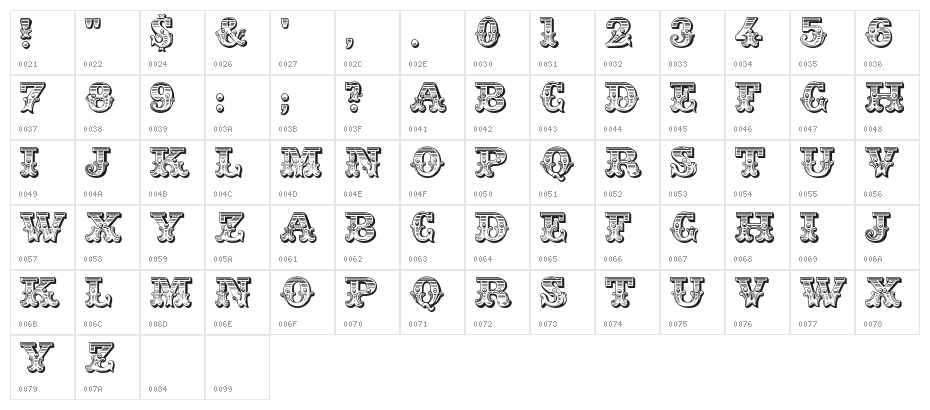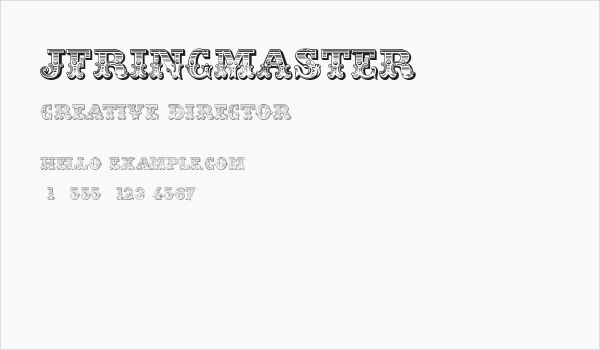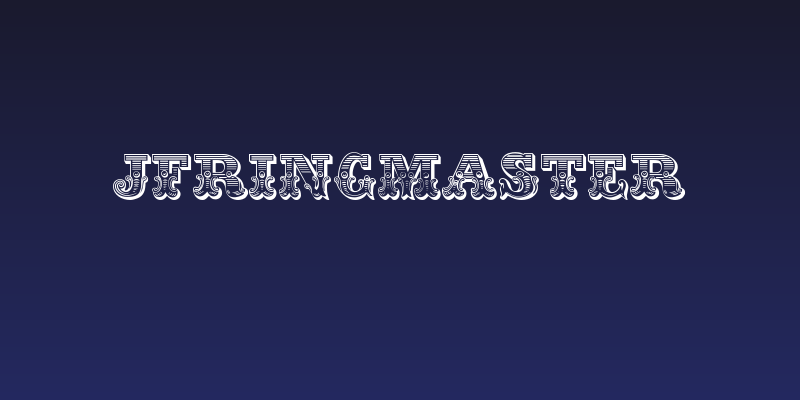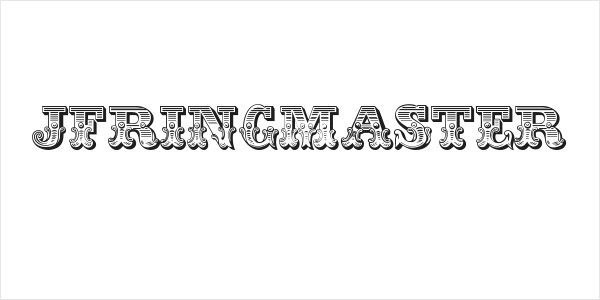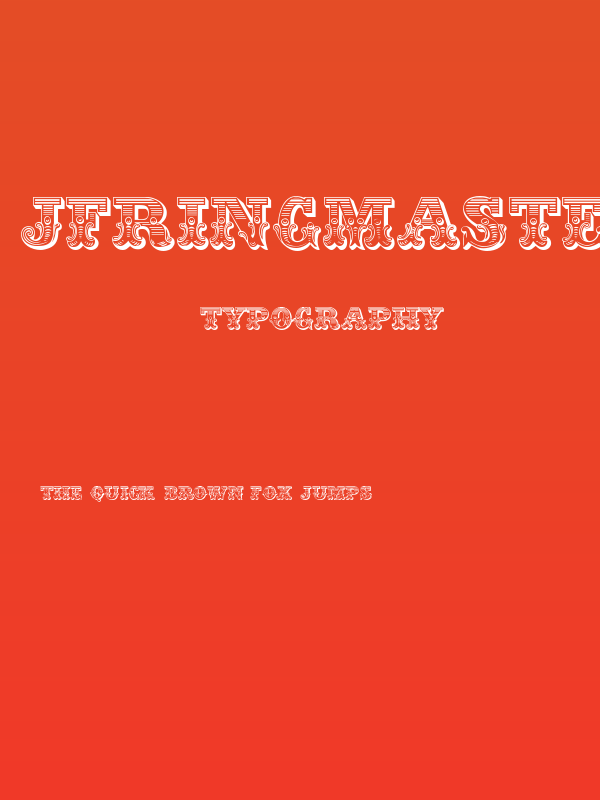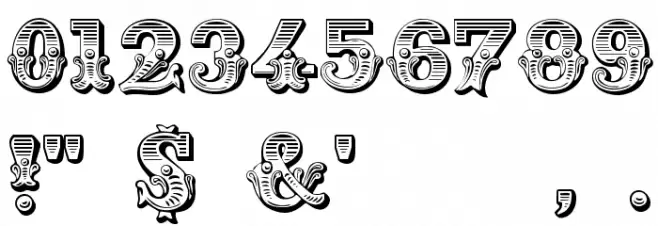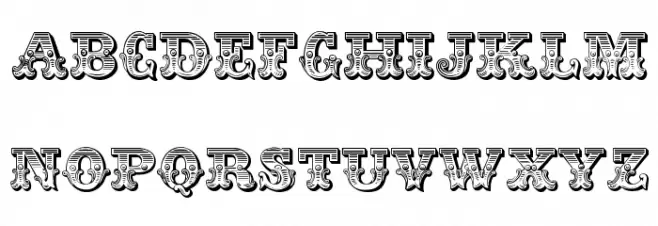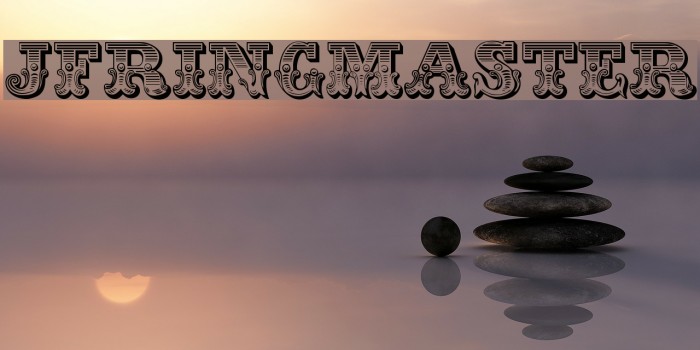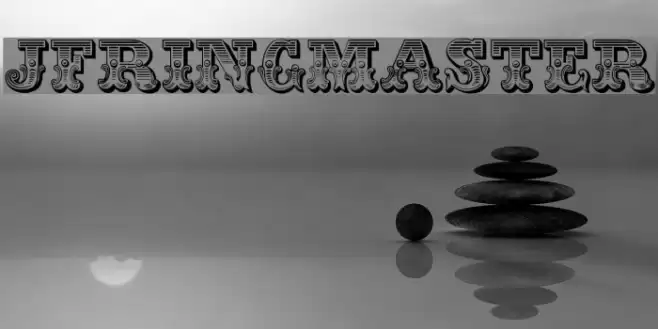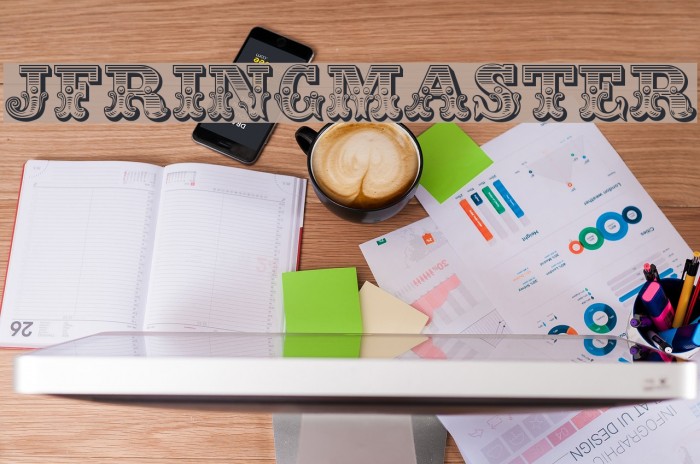
JFRingmaster Font
| Progetti proposti | Ideal for circus-themed posters, vintage-style advertisements, theatrical event flyers, and any design requiring a dramatic, nostalgic touch. |